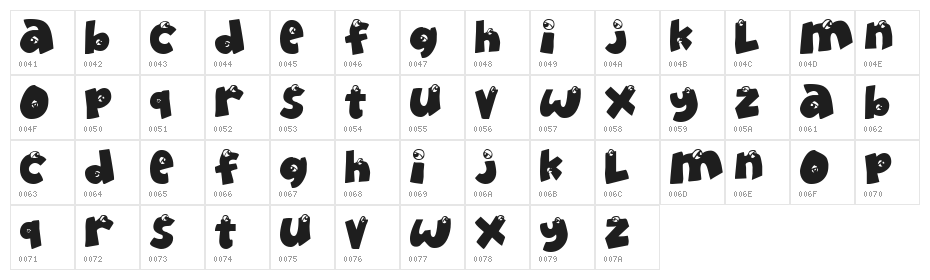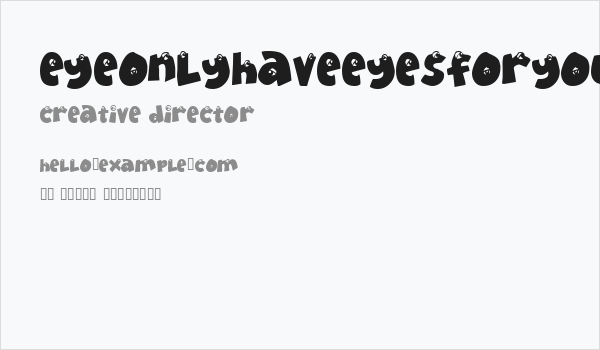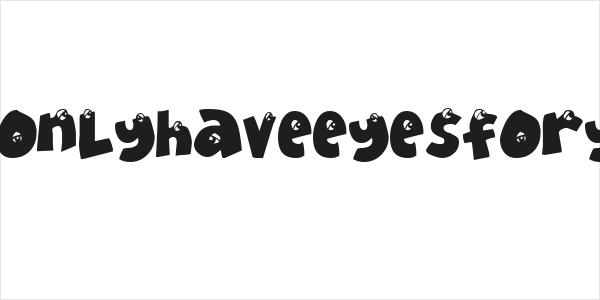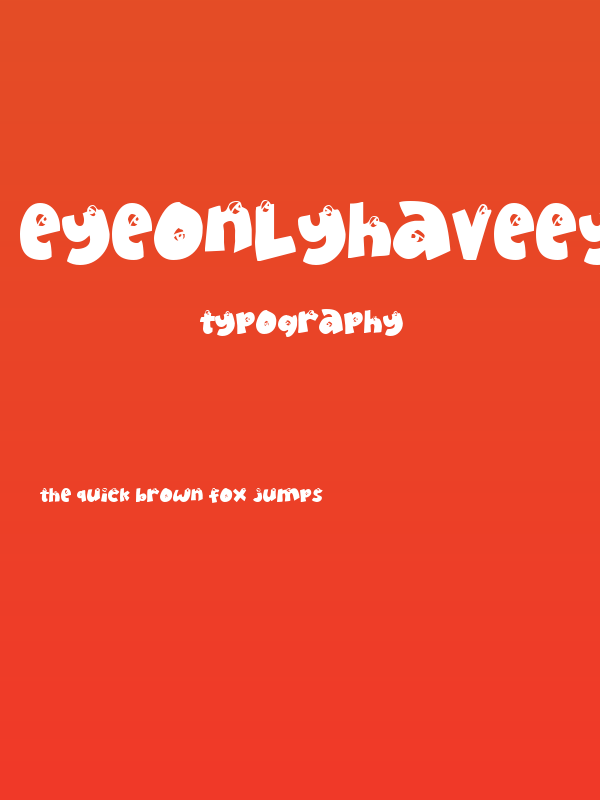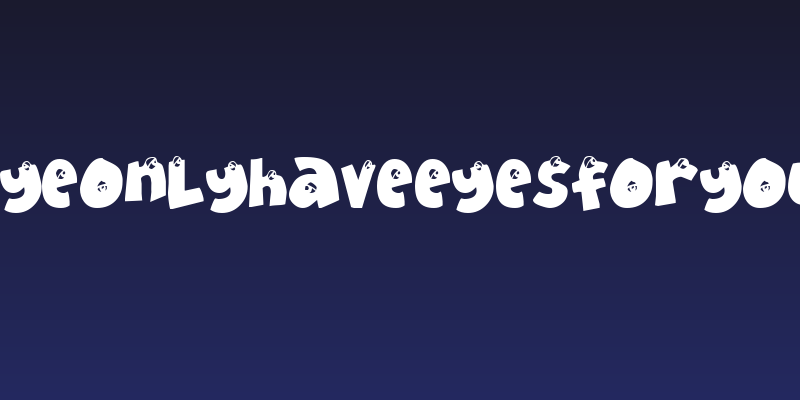
EyeOnlyHaveEyesForYou Font
| Stile generale | Playful, Whimsical |
| Progetti proposti | Ideal for children's books, playful branding, comic strips, or any project requiring a fun and lively typeface. |